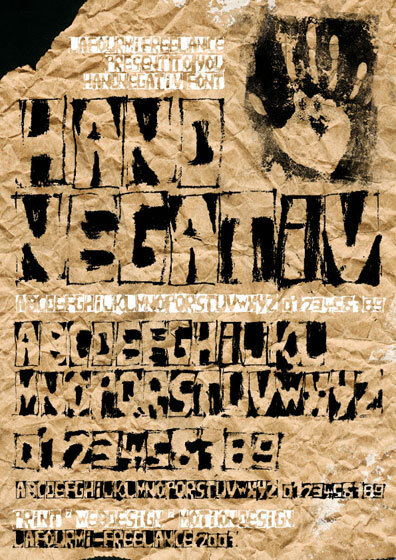
Hand Negativ von Lafourmi ist eine kostenlose Display-Schrift im Holzschnitt-Stil mit einem rauen, handgezeichneten Look. Die Buchstaben wirken wie aus zerschundenen Holzblöcken geschnitten, mit ausgefransten Kanten, unebenen Flächen und einer körnigen Drucktextur, die die Großbuchstaben eher wie plakative Grafik als poliertes Design wirken lässt.
Ideal für Artworks, die eine rohe, menschliche Note brauchen – Indie-Konzertflyer, Zine-Cover, Horror-Titel, Streetwear-Grafiken und auffällige Verpackungen. Als kostenloser Font eignet sich HandNegativ am besten für kurze Überschriften, Monogramme und logo-artige Schriftzüge, bei denen die kantigen, blockartigen Formen für sich sprechen können.